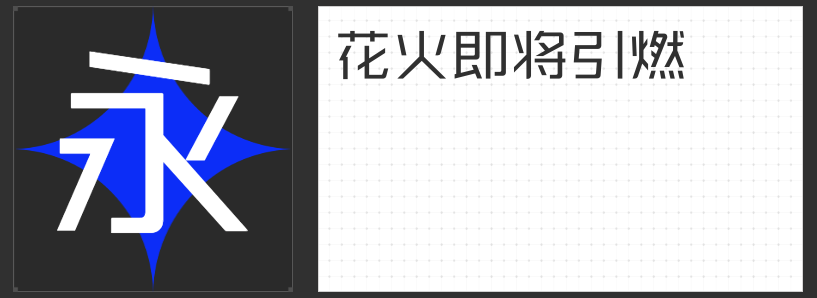
笔触破界:四款创意字体重构设计视觉张力
在当代设计中,字体的角色早已超越信息载体,成为传递情绪、塑造空间、构建叙事的核心语言。以下四款创意字体,以独特的形态逻辑与美学表达,为设计注入鲜活的生命力,重新定义文字的视觉可能性。
一、字恋狂风摇简 粗体
这款字体以“风”为灵感,通过笔画摇摆的动态轨迹与夸张的失衡比例,模拟纸张被疾风掀动的瞬间。看似无序的歪斜结构中,暗藏精密的视觉重心计算——每个字符的倾斜角度与重心偏移均经过反复调整,确保在恣意挥洒中仍保持可读性。其手写般的拙朴质感,既传递温暖的人文气息,又以打破常规的形态激发观者的想象,适合需要营造轻松氛围或强调动态感的设计场景。
二、字恋狂漫野 鸣风
以直线为核心构建的“鸣风”,通过去钩化处理与笔画断裂设计,剥离传统手写字体的冗余装饰,保留最本质的书写韵律。字符间细微的大小差异与通透的布白空间,形成类似音乐节拍的视觉律动,使版面在静态中蕴含动态势能。其灰度均匀的笔画设计,既保证远距离阅读的清晰度,又以克制的形态语言传递现代感,尤其适合需要兼顾功能性与艺术性的设计表达。
三、励字勇敢黑简 常规
作为无衬线字体的革新之作,“勇敢黑”以粗壮笔划与几何化结构构建视觉重量感。撇捺的钝角处理与横竖的均匀分布,消除传统黑体的机械感,赋予文字沉稳而不失亲和的气质。其极简的形态语言,使字体在远距离仍能保持高辨识度,成为标题、标志等需要强化视觉冲击力的场景中的理想选择,以克制的形态传递坚定的力量感。
四、励字磅礴简 超黑
“磅礴黑”以颠覆性的斜正融合设计,打破字体结构的静态平衡。左侧倾斜的笔划如山峦层叠,右侧垂直的架构似磐石稳固,二者碰撞产生强烈的视觉张力。这种矛盾统一的形态语言,既保留黑体的庄重感,又通过动态倾斜赋予文字向前奔涌的势能,适合需要营造宏大叙事或强调突破性的设计语境,以字形重构空间维度。
这四款字体共同诠释了当代字体设计的核心趋势——从形态模仿转向情绪表达,从功能满足升级为空间塑造。它们以或恣意、或克制、或矛盾的形态语言,证明字体不仅是设计工具,更是能够独立承载美学价值的视觉符号。在信息过载的今天,这些充满实验精神的字体,正以独特的姿态为设计注入不可复制的灵魂。